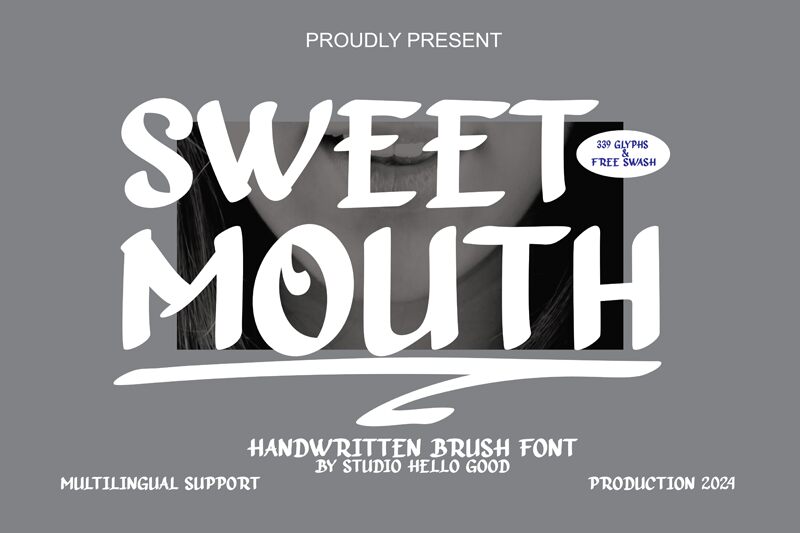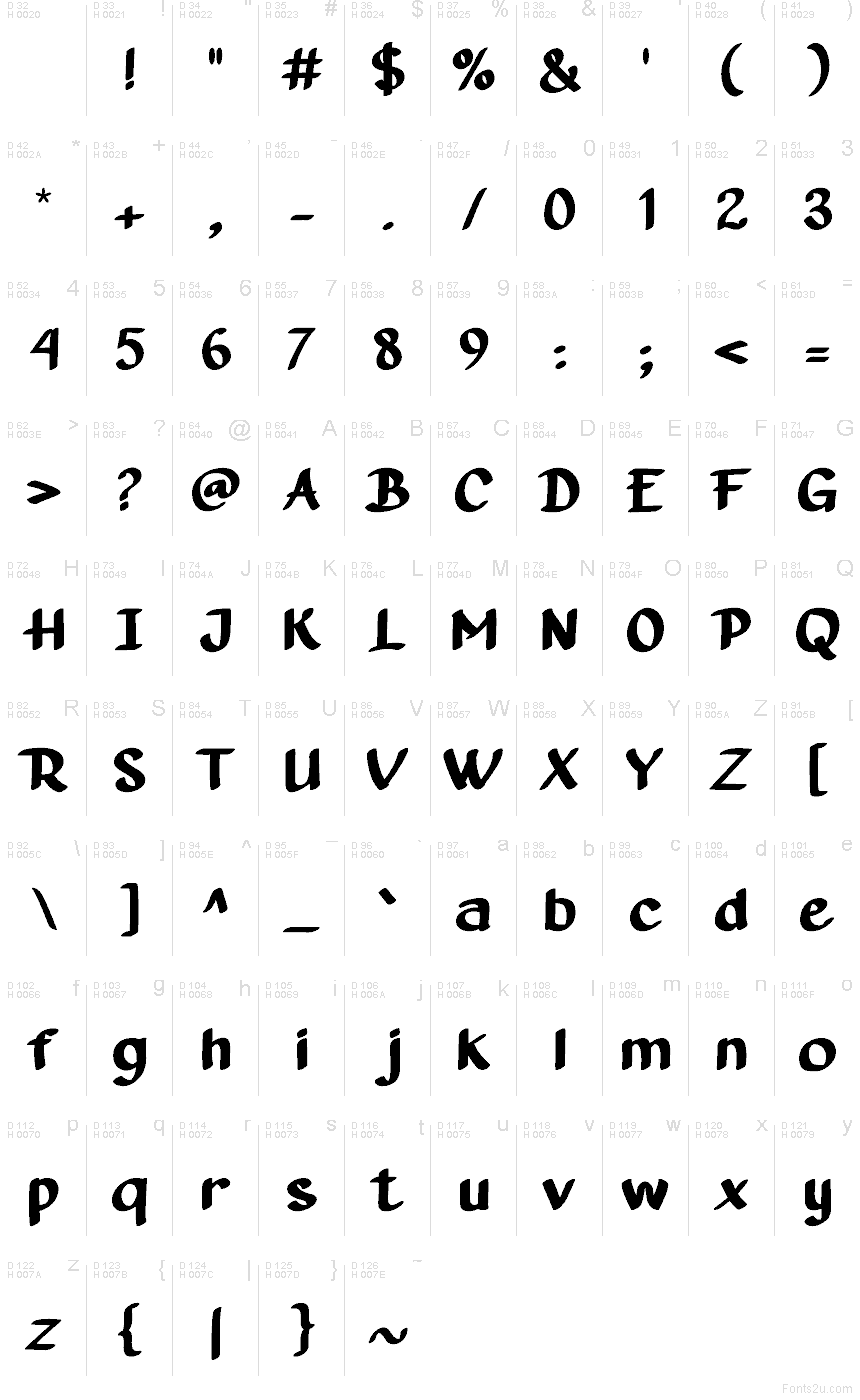
SWEET MOUTH
Sweet Mouth від Hello Good Studio — це безкоштовний рукописний акцидентний шрифт із широкими штрихами, що нагадують мазки пензля, та заокругленими, нерівними краями. Його знаки виглядають намальованими від руки, а не вивіреними: м’які вигини, нахил та невимушений ритм надають шрифту виразного, дещо грубуватого вигляду.
Sweet Mouth чудово підходить для дизайну логотипів, пакування, заголовків плакатів, меню кафе та графіки для соціальних мереж, оскільки його живі штрихи створюють виразний рукописний акцент, не виглядаючи при цьому надто формально. Цей безкоштовний шрифт також ідеально підійде брендам, яким потрібен крафтовий або особистий підхід, особливо якщо потрібно зробити акцент на заголовку або короткій цитаті, яка має звучати неформально та прямо.